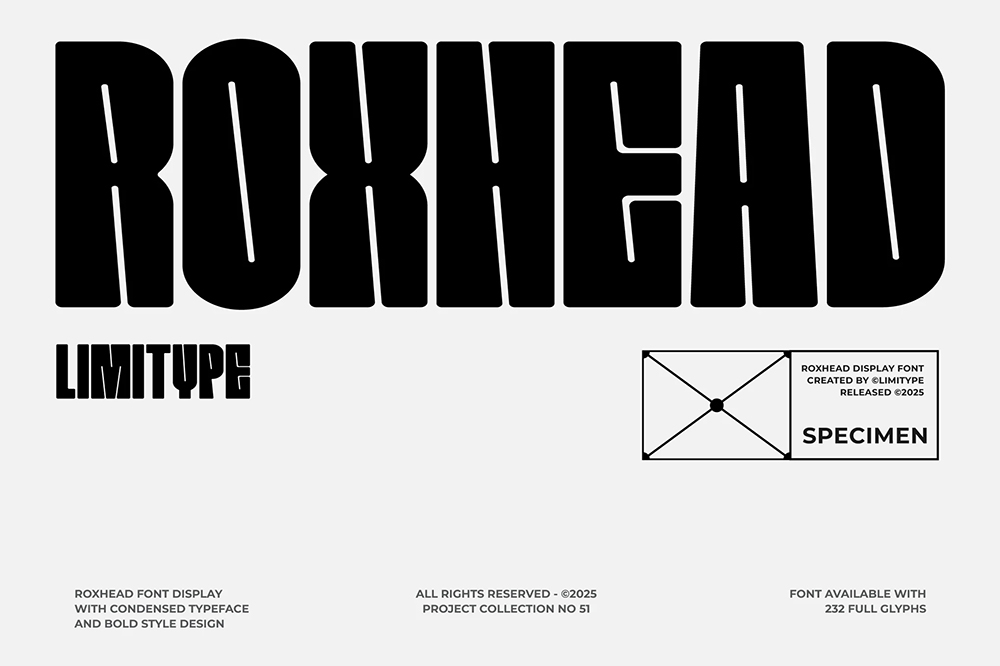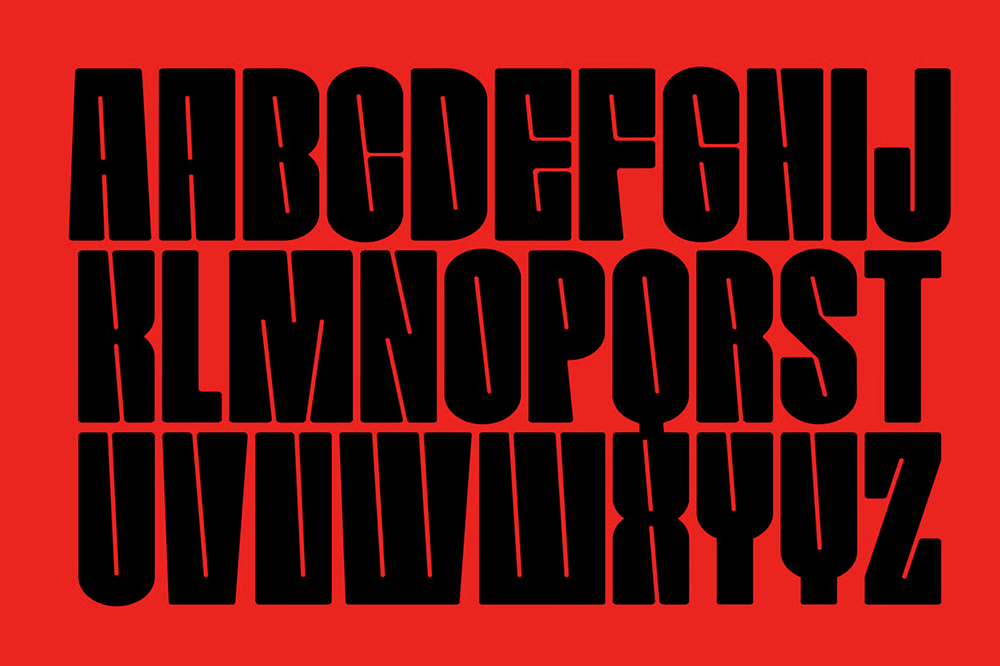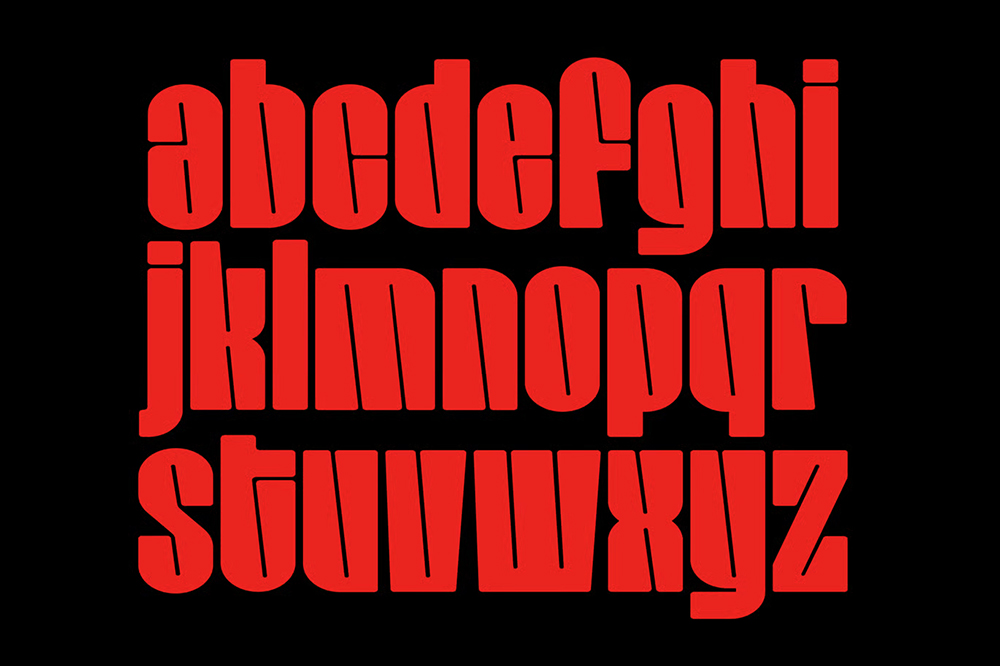
فونت پرمیوم و انگلیسی Roxhead Font یک فونت شهری مدرن با سبکی جمع و جور و جزئیات ظریف روی کابینت است. این فونت برای تیترها، پوسترها، مجلات و کالاهایی که ظاهری مدرن و شهری دارند، کاملاً مناسب است.